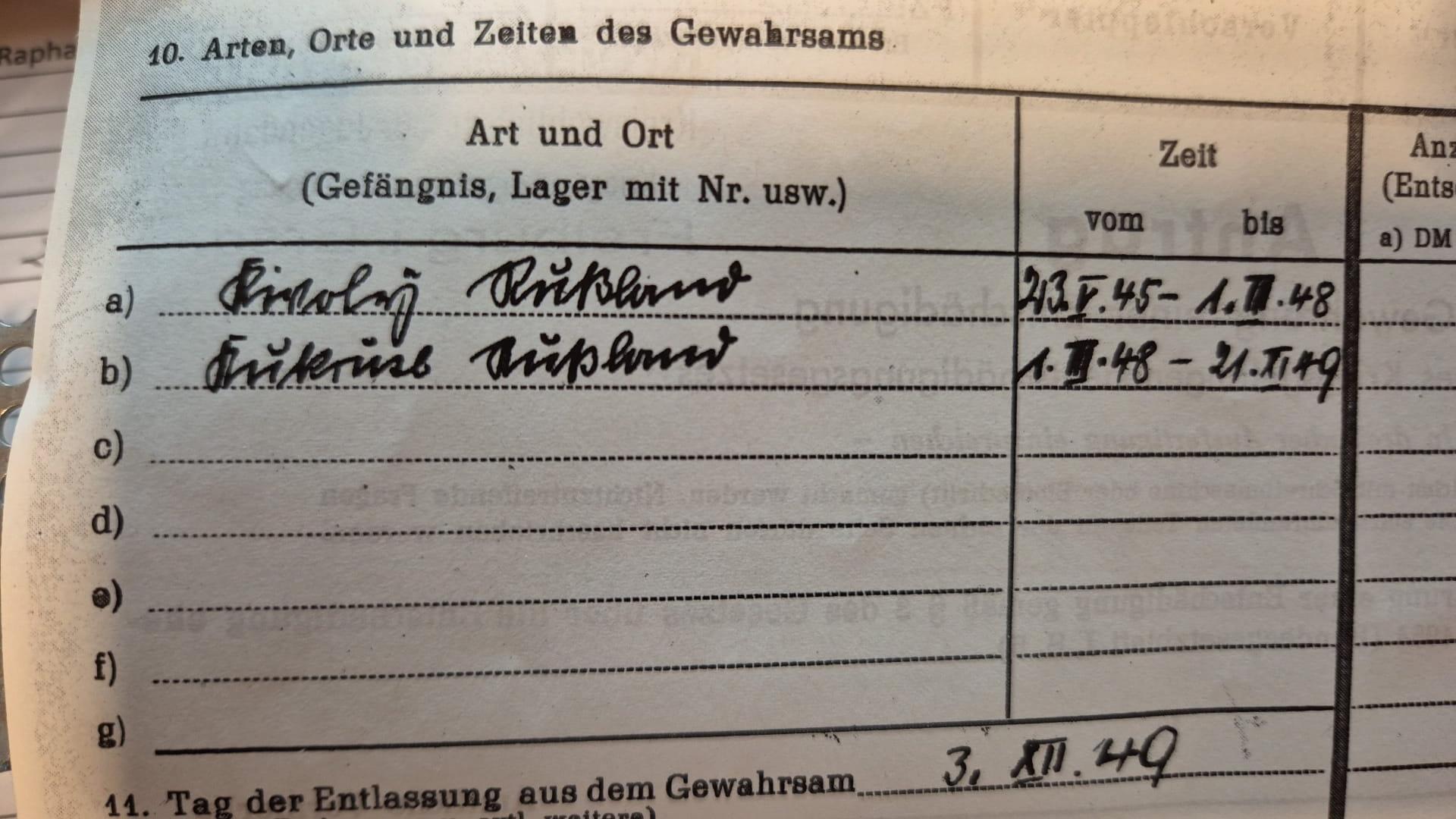
Ortschaftsnamen entziffern Sütterlinschrift
ich habe ein Dokument indem mein Opa eingetragen hat wo er in Kriegsgefangenschaft nach dem 2. Weltkrieg war. Leider gibt es niemanden mehr der das noch genau weiß oder lesen kann.
Er war in Rußland soviel weiß ich. Das müsste auch das jeweils zweite Wort sein. Die eigentlichen Ortsnamen kann ich nicht entziffern.
Wenn ich nich komplett falsch liege müssten beide mir "K" beginnen und beim zweiten ist der zweite Buchstabe ein "u"?
Kann mir jemadn helfen und die Ortsnamen lesen?
Das zweite Wort ist größtenteils in lateinischer Schrift: "Nach dem Zweiten Weltkrieg befand sich in Kukruse ein sowjetisches Kriegsgefangenenlager für ehemalige Angehörige der Wehrmacht."
Der erste Ort ist in Kurrentschrift geschrieben. Das geschriebene Wort ist "Kivoly". Es handelt sich sehr wahrscheinlich um diesen Ort.
Das würde auch zu seinem Einsatzort passen. Seine Einheit war zuletzt in Kurland eingesetzt.
PS:Von Kurrentschrift, habe ich vorher noch nie was gehört.-?